Font chữ miễn phí ngày nay không còn là lựa chọn “tạm dùng” cho các dự án tiết kiệm ngân sách. Nhiều bộ font sở hữu chất lượng thiết kế, khả năng đọc, hỗ trợ đa ngôn ngữ và giấy phép sử dụng rất tốt, đủ sức thay thế font trả phí trong branding, website, social media, bao bì, portfolio và ấn phẩm quảng cáo.
Tổng Hợp Font Chữ Miễn Phí Cực Xịn Không Thua Kém Font Trả Phí
Vì sao font miễn phí ngày càng được designer chuyên nghiệp lựa chọn
Trong nhiều năm, font miễn phí thường bị gắn với định kiến thiếu tinh chỉnh, ít trọng lượng, kerning chưa tốt hoặc không phù hợp cho dự án thương mại. Tuy nhiên, thị trường typography đã thay đổi rất nhanh. Các studio độc lập, nền tảng phân phối font mở và cộng đồng thiết kế toàn cầu đã tạo ra nhiều bộ chữ miễn phí có chất lượng cao, được cập nhật thường xuyên và có giấy phép rõ ràng.
Điểm mạnh lớn nhất của font miễn phí hiện đại là khả năng tiếp cận. Một freelancer, startup, nhà sáng tạo nội dung hoặc đội marketing nhỏ vẫn có thể xây dựng hệ thống nhận diện chỉn chu mà không cần đầu tư quá nhiều chi phí ban đầu. Điều này đặc biệt quan trọng với các dự án cần thử nghiệm nhanh nhiều hướng thiết kế trước khi chốt phong cách chính thức.
Nhiều font miễn phí còn được phát triển theo triết lý open source, nghĩa là cộng đồng có thể đóng góp, sửa lỗi, mở rộng bảng ký tự và cải thiện khả năng hiển thị trên nhiều thiết bị. Nhờ đó, một số bộ font miễn phí không chỉ đẹp về hình thức mà còn rất ổn định khi dùng trên website, ứng dụng, tài liệu số và giao diện sản phẩm.
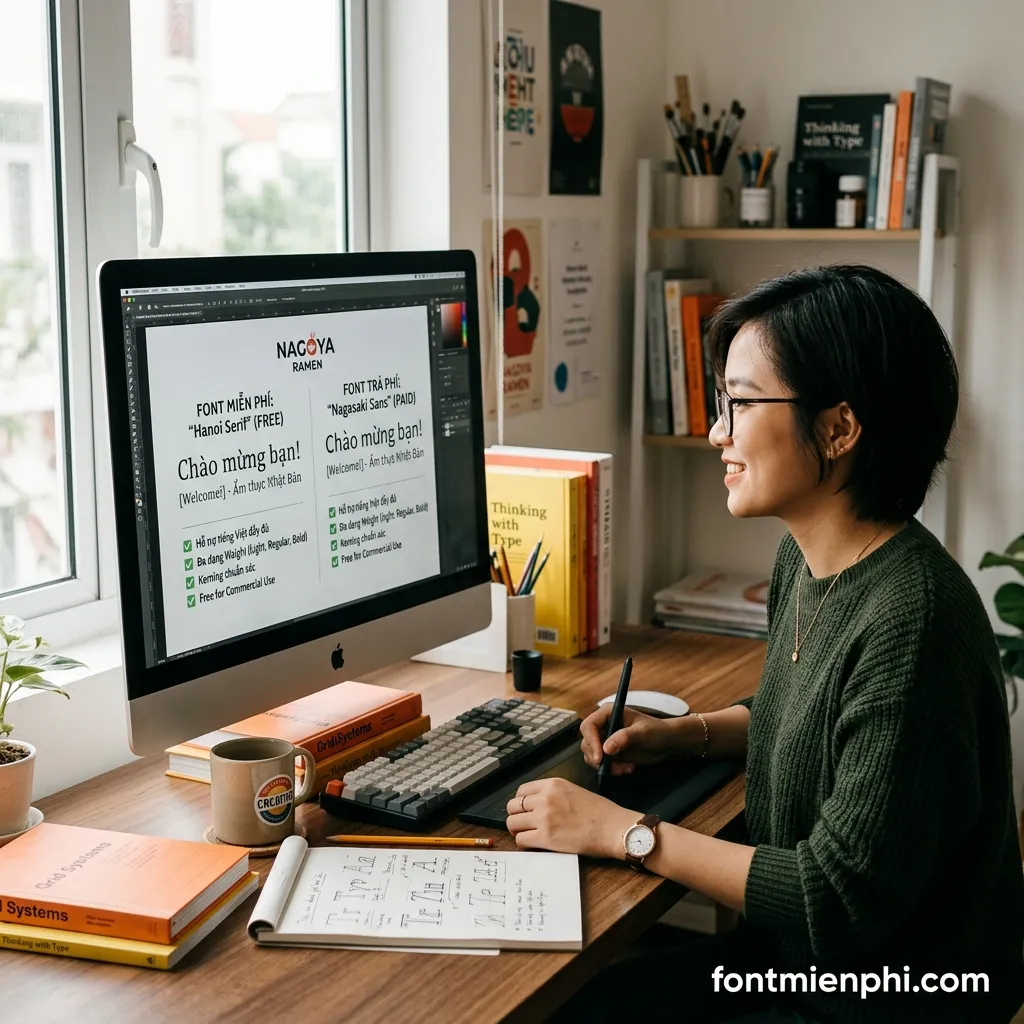
Tiêu chí đánh giá một font miễn phí có đủ “xịn” hay không
Một font miễn phí đáng dùng không chỉ nằm ở cảm giác đẹp khi nhìn lướt qua. Designer chuyên nghiệp thường đánh giá font dựa trên nhiều yếu tố: độ dễ đọc, khoảng cách chữ, độ cân bằng giữa các ký tự, số lượng weight, hỗ trợ tiếng Việt, giấy phép thương mại và tính linh hoạt trong các bối cảnh ứng dụng khác nhau.
Với thị trường Việt Nam, hỗ trợ tiếng Việt là tiêu chí cực kỳ quan trọng. Một font đẹp nhưng thiếu dấu tiếng Việt hoặc hiển thị dấu không cân đối sẽ gây mất chuyên nghiệp ngay lập tức. Khi chọn font, cần kiểm tra kỹ các ký tự như ă, â, ê, ô, ơ, ư, đ và những tổ hợp dấu nặng, hỏi, ngã, sắc, huyền trong câu dài.
Khi nào nên dùng font miễn phí thay vì mua font trả phí
Font miễn phí rất phù hợp với các dự án cần tốc độ triển khai, ngân sách hạn chế hoặc đang ở giai đoạn thử nghiệm phong cách. Ví dụ, một landing page chạy chiến dịch ngắn hạn, bộ template mạng xã hội, bài thuyết trình thương hiệu, blog cá nhân, hồ sơ năng lực freelancer hoặc dự án MVP đều có thể tận dụng font miễn phí chất lượng cao.
Tuy nhiên, điều đó không có nghĩa font miễn phí chỉ dành cho dự án nhỏ. Nhiều thương hiệu lớn vẫn sử dụng font open source vì tính ổn định, khả năng nhúng web thuận tiện và hiệu suất tốt. Các bộ font như Inter, Source Sans, IBM Plex, Noto Sans hay Montserrat đã xuất hiện trong vô số sản phẩm số chuyên nghiệp trên toàn thế giới.
Font trả phí vẫn có lợi thế ở tính độc quyền, chất lượng hoàn thiện rất sâu, nhiều biến thể đặc biệt và dịch vụ hỗ trợ từ foundry. Nhưng nếu mục tiêu là tạo ra thiết kế đẹp, rõ ràng, hiện đại và dễ triển khai, một bộ font miễn phí được chọn đúng hoàn toàn có thể mang lại kết quả không thua kém font thương mại.
Nhóm Font Sans Serif Miễn Phí Cho Website, App Và Nhận Diện Hiện Đại
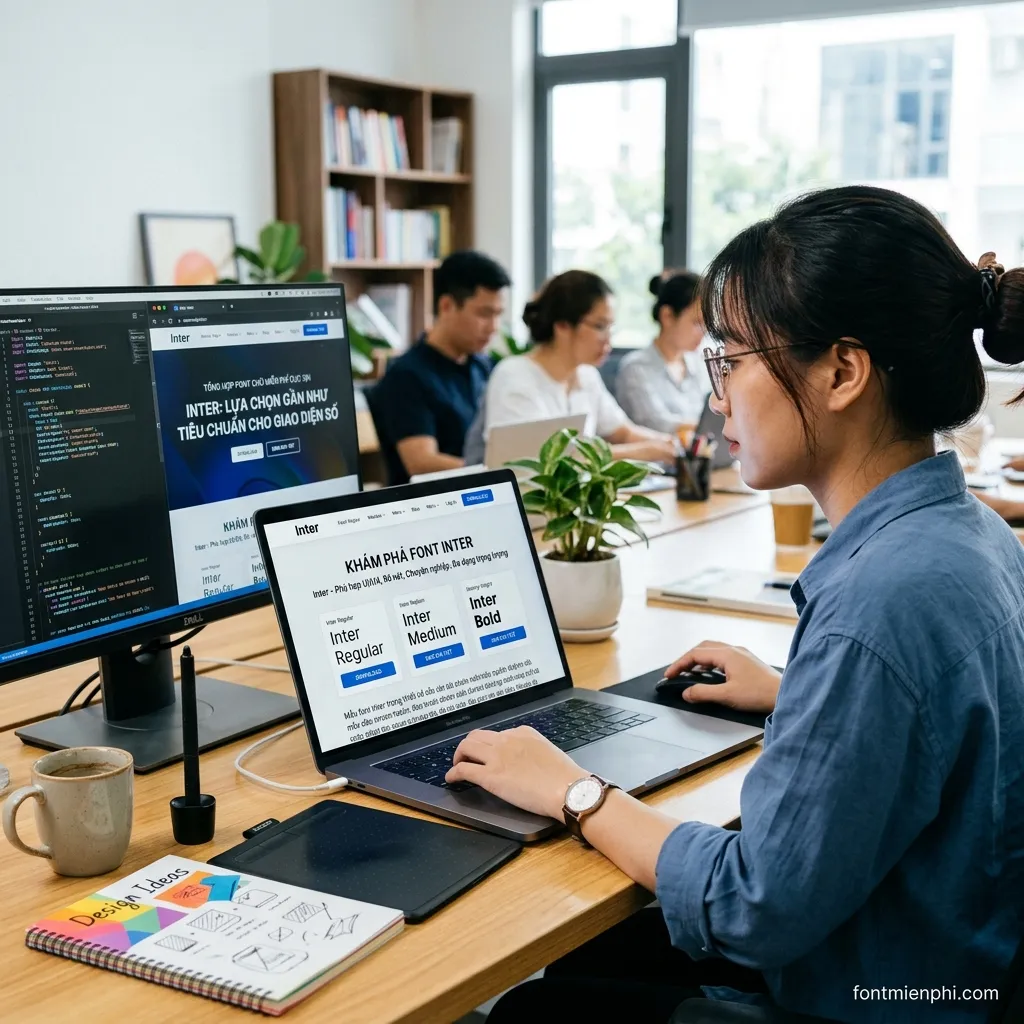
Inter: lựa chọn gần như tiêu chuẩn cho giao diện số
Inter là một trong những font sans serif miễn phí nổi bật nhất hiện nay, đặc biệt phù hợp cho website, dashboard, ứng dụng SaaS, mobile app và hệ thống thiết kế. Font được tối ưu cho màn hình, có độ cao chữ hợp lý, khoảng cách thoáng và khả năng đọc tốt ở kích thước nhỏ. Đây là lý do Inter thường được xem như lựa chọn an toàn nhưng vẫn rất chuyên nghiệp.
Điểm đáng giá của Inter là bộ weight phong phú, hỗ trợ variable font và hoạt động hiệu quả trong nhiều cấp độ nội dung, từ menu, button, form label đến tiêu đề lớn. Khi dùng cho giao diện sản phẩm, Inter giúp tổng thể trở nên gọn gàng, trung tính và đáng tin cậy, không lấn át nội dung nhưng vẫn giữ được cảm giác hiện đại.
– Phù hợp với website công nghệ, SaaS, fintech, dashboard, mobile app
– Ưu điểm nổi bật là dễ đọc, nhiều weight, hỗ trợ web tốt
– Nên dùng khi cần một font trung tính, sạch, ít rủi ro về thẩm mỹ
Manrope: tối giản nhưng có cá tính hơn font UI thông thường
Manrope là font sans serif miễn phí có phong cách hiện đại, tối giản nhưng không quá lạnh. So với nhiều font giao diện phổ biến, Manrope có cấu trúc hình học rõ hơn, đường nét mở và cảm giác thân thiện. Font này rất hợp với thương hiệu công nghệ, giáo dục trực tuyến, sản phẩm tài chính trẻ trung hoặc các landing page muốn tạo ấn tượng cao cấp.
Manrope hoạt động tốt ở cả tiêu đề lẫn đoạn văn. Khi dùng cho heading, font tạo cảm giác chắc chắn và gọn gàng. Khi dùng cho body text, nó vẫn giữ được độ đọc ổn nếu thiết lập line-height hợp lý. Với tiếng Việt, Manrope hỗ trợ khá tốt và có thể dùng trong nhiều dự án thương mại mà không cần lo lắng về chi phí bản quyền.
Để Manrope phát huy hiệu quả, nên kết hợp với bố cục rộng rãi, nhiều khoảng trắng và bảng màu tinh giản. Font này không cần quá nhiều hiệu ứng trang trí; chính sự cân bằng giữa hình học và độ mềm vừa phải đã đủ tạo nên cảm giác cao cấp.
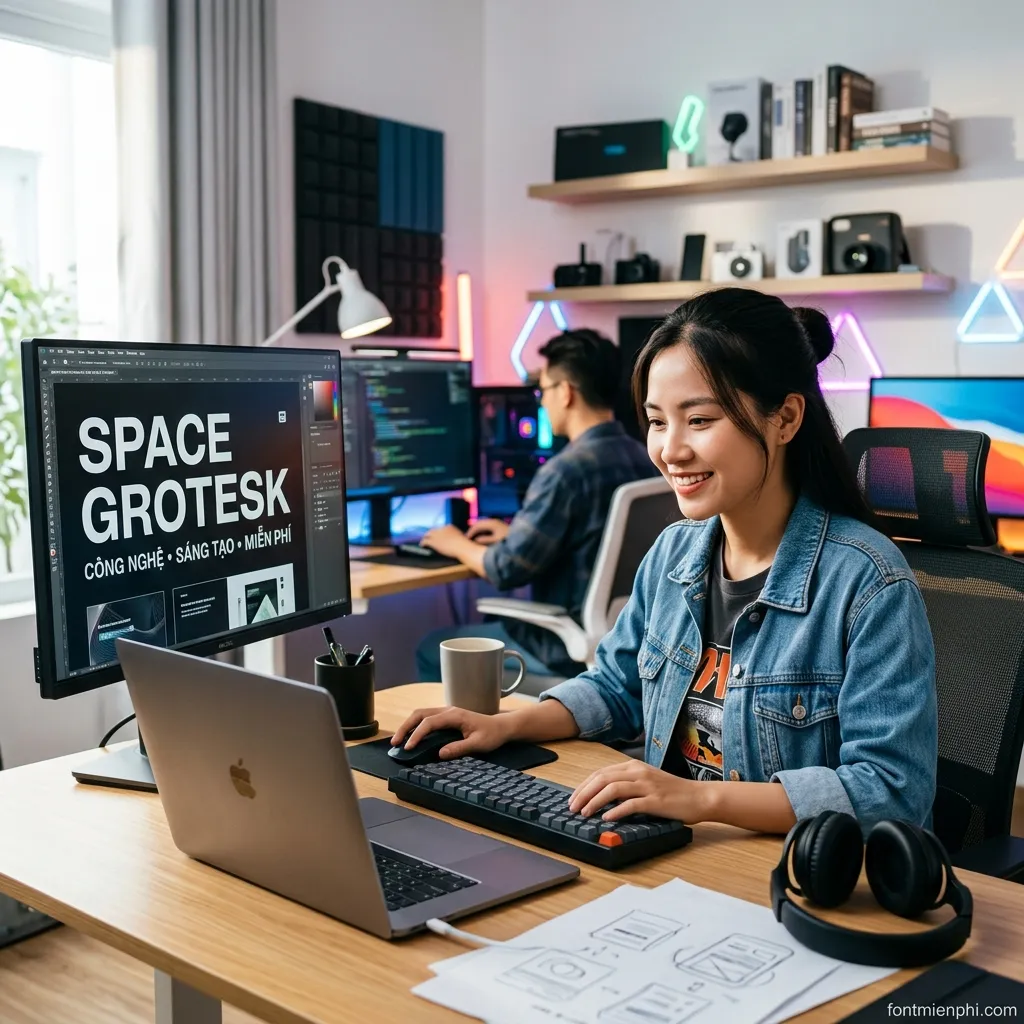
Space Grotesk: font miễn phí có chất công nghệ và sáng tạo
Space Grotesk là lựa chọn tuyệt vời khi bạn muốn thiết kế mang tinh thần tương lai, công nghệ, sáng tạo hoặc hơi experimental nhưng vẫn đảm bảo khả năng đọc. Font có dáng chữ rộng, một số chi tiết đặc trưng ở ký tự tạo cảm giác khác biệt so với các sans serif thông thường. Đây là font rất hợp cho tiêu đề, poster kỹ thuật số, portfolio sáng tạo và website studio.
Khi dùng Space Grotesk, nên chú ý không lạm dụng ở đoạn văn quá dài nếu kích thước chữ nhỏ. Font này tỏa sáng nhất ở headline, navigation, hero section, card title hoặc quote ngắn. Có thể kết hợp Space Grotesk cho tiêu đề với một font body trung tính hơn như Source Sans 3, Noto Sans hoặc IBM Plex Sans để cân bằng giữa cá tính và độ dễ đọc.
– Phù hợp với portfolio, agency, startup AI, sản phẩm sáng tạo
– Nên dùng cho tiêu đề lớn, hero text, poster, banner và social media
– Có thể tạo cảm giác cao cấp nếu đi cùng màu sắc tối giản và layout mạnh
IBM Plex Sans: chuyên nghiệp, đáng tin cậy và giàu tính hệ thống
IBM Plex Sans là một phần trong hệ font IBM Plex nổi tiếng, được thiết kế để thể hiện tinh thần công nghệ, kỹ thuật và sự minh bạch. Đây là font miễn phí có chất lượng rất cao, nhiều weight, hỗ trợ nhiều ngôn ngữ và phù hợp với những thương hiệu cần cảm giác nghiêm túc, đáng tin cậy nhưng không cứng nhắc.
Ưu điểm của IBM Plex Sans là khả năng xây dựng hệ thống typography đồng bộ. Bạn có thể dùng IBM Plex Sans cho giao diện, IBM Plex Serif cho nội dung editorial và IBM Plex Mono cho code hoặc dữ liệu kỹ thuật. Sự thống nhất giữa các biến thể giúp thương hiệu có chiều sâu hơn mà vẫn tiết kiệm chi phí.
Trong các dự án B2B, tài chính, công nghệ, giáo dục hoặc tài liệu chuyên môn, IBM Plex Sans mang lại cảm giác rất “đúng chỗ”. Nó không quá thời trang để nhanh lỗi mốt, cũng không quá phổ thông đến mức nhạt nhòa. Đây là lựa chọn đáng cân nhắc nếu bạn cần một font miễn phí có độ tin cậy cao.
Nhóm Font Serif Và Display Miễn Phí Cho Thương Hiệu Cao Cấp
Playfair Display: vẻ đẹp editorial cho tiêu đề sang trọng
Playfair Display là font serif miễn phí rất nổi tiếng, thường được dùng cho thời trang, mỹ phẩm, nghệ thuật, nhà hàng cao cấp, wedding branding và các thiết kế cần cảm giác thanh lịch. Font có độ tương phản nét cao, dáng chữ mềm mại và tạo ấn tượng mạnh khi đặt ở kích thước lớn.
Điểm cần lưu ý là Playfair Display không phải lựa chọn tối ưu cho đoạn văn dài trên màn hình nhỏ. Font phù hợp hơn cho headline, quote, logo dạng chữ, bìa catalogue hoặc tiêu đề section. Khi kết hợp với sans serif hiện đại như Lato, Source Sans 3 hoặc Work Sans, Playfair Display có thể tạo nên cặp typography cân bằng giữa cổ điển và hiện đại.
Với tiếng Việt, cần kiểm tra kỹ từng phiên bản và nguồn tải để đảm bảo dấu hiển thị đẹp. Trong thiết kế thương hiệu cao cấp, chỉ một dấu tiếng Việt bị lệch hoặc quá sát ký tự cũng có thể làm giảm đáng kể cảm giác chuyên nghiệp của toàn bộ ấn phẩm.
Cormorant Garamond: tinh tế, cổ điển và giàu cảm xúc
Cormorant Garamond là font serif miễn phí lấy cảm hứng từ phong cách Garamond cổ điển, nhưng được diễn giải theo hướng sắc sảo và giàu tính trình diễn hơn. Font này đặc biệt phù hợp với các dự án văn hóa, nghệ thuật, xuất bản, thương hiệu thủ công, thời trang boutique và thiết kế cần chiều sâu thẩm mỹ.
Khi dùng Cormorant Garamond, nên khai thác các weight nhẹ hoặc semi-bold cho tiêu đề lớn để tạo cảm giác tinh tế. Font có nét thanh mảnh, độ tương phản cao nên cần tránh đặt trên nền quá phức tạp hoặc dùng kích thước quá nhỏ. Với layout phù hợp, Cormorant Garamond có thể tạo cảm giác đắt tiền không kém nhiều font serif thương mại.
– Phù hợp với thương hiệu nghệ thuật, thời trang, sách, văn hóa, thủ công
– Nên dùng trong heading, quote, logo chữ, tiêu đề catalogue
– Kết hợp tốt với sans serif đơn giản để tránh tổng thể bị quá cổ điển
Bodoni 72 và Libre Bodoni: chất thời trang mạnh mẽ
Bodoni là phong cách serif kinh điển gắn liền với thời trang, tạp chí, mỹ phẩm và thiết kế luxury. Trong nhóm font miễn phí, Libre Bodoni là lựa chọn đáng chú ý nhờ giữ được tinh thần tương phản cao, nét dọc mạnh và vẻ ngoài sang trọng. Nếu muốn tạo headline có cảm giác thời thượng, Libre Bodoni có thể là một phương án rất hiệu quả.
Tuy nhiên, font kiểu Bodoni cần được dùng có kiểm soát. Độ tương phản nét quá cao khiến chữ dễ mất chi tiết khi in nhỏ hoặc hiển thị trên màn hình độ phân giải thấp. Vì vậy, nên ưu tiên dùng cho tiêu đề lớn, logo, poster, bìa lookbook hoặc các điểm nhấn thị giác thay vì dùng cho body text dài.
Khi phối Libre Bodoni với một sans serif tối giản, thiết kế sẽ có sự căng đối thú vị giữa cổ điển và hiện đại. Đây là công thức phổ biến trong ngành thời trang: serif cao cấp cho cảm xúc thương hiệu, sans serif sạch cho thông tin chức năng.
Abril Fatface: nổi bật, đậm chất poster và rất dễ ghi nhớ
Abril Fatface là font display miễn phí có cá tính mạnh, nét dày, độ tương phản cao và khả năng tạo điểm nhấn tức thì. Font này phù hợp với tiêu đề quảng cáo, poster sự kiện, banner mạng xã hội, bìa blog hoặc các thiết kế cần thu hút ánh nhìn trong thời gian ngắn.
Khác với những font serif thanh lịch, Abril Fatface mang cảm giác táo bạo và giàu năng lượng hơn. Nó có thể làm một layout đơn giản trở nên nổi bật chỉ bằng một dòng tiêu đề lớn. Tuy nhiên, vì cá tính quá rõ, font này nên được dùng tiết chế. Nếu dùng quá nhiều, thiết kế dễ trở nên nặng nề và khó đọc.
– Phù hợp với poster, campaign, social media, tiêu đề blog, sự kiện
– Nên dùng ở kích thước lớn với số lượng chữ vừa phải
– Kết hợp tốt với sans serif nhẹ, khoảng trắng lớn và màu nền có chủ đích
Nhóm Font Miễn Phí Hỗ Trợ Tiếng Việt Tốt Cho Nội Dung Dài
Noto Sans và Noto Serif: giải pháp an toàn cho dự án đa ngôn ngữ
Noto là hệ font miễn phí do Google phát triển với mục tiêu hỗ trợ gần như toàn bộ hệ chữ trên thế giới. Với tiếng Việt, Noto Sans và Noto Serif là hai lựa chọn rất đáng tin cậy vì dấu hiển thị ổn định, ký tự đầy đủ và khả năng đọc tốt trong nhiều môi trường khác nhau.
Noto Sans phù hợp với website tin tức, blog, tài liệu hướng dẫn, giao diện ứng dụng và các hệ thống cần độ rõ ràng cao. Noto Serif phù hợp hơn với bài viết dài, nội dung học thuật, xuất bản số hoặc những dự án muốn tạo cảm giác nghiêm túc, truyền thống hơn. Cả hai đều không quá phô diễn, nhưng chính sự trung tính đó lại giúp nội dung trở thành trung tâm.
Đối với SEO và trải nghiệm đọc, một font ổn định như Noto có giá trị rất lớn. Người dùng ở các thiết bị khác nhau vẫn thấy chữ rõ, dấu không lỗi và đoạn văn không bị vỡ nhịp. Đây là yếu tố thường bị xem nhẹ, nhưng lại ảnh hưởng trực tiếp đến thời gian ở lại trang và khả năng tiếp nhận nội dung.
Source Sans 3: cân bằng giữa thân thiện và chuyên nghiệp
Source Sans 3 là phiên bản phát triển từ Source Sans Pro, một font sans serif miễn phí rất được ưa chuộng trong thiết kế giao diện và nội dung số. Font có dáng chữ mở, khoảng cách dễ chịu, hỗ trợ nhiều weight và hiển thị tốt ở kích thước nhỏ. Đây là lựa chọn phù hợp cho website doanh nghiệp, blog chuyên môn, trang dịch vụ và tài liệu trực tuyến.
So với một số font geometric sans, Source Sans 3 có cảm giác nhân văn và dễ đọc hơn trong đoạn văn dài. Nó không gây mỏi mắt, không quá cá tính và hoạt động tốt với nhiều ngành nghề. Nếu bạn cần một font body đáng tin cậy để đi cùng display font mạnh ở phần tiêu đề, Source Sans 3 là lựa chọn rất thực tế.
– Phù hợp với blog, website doanh nghiệp, tài liệu, landing page, app
– Ưu điểm là dễ đọc, trung tính, hỗ trợ tiếng Việt tốt
– Có thể kết hợp với Playfair Display, Space Grotesk hoặc Cormorant Garamond
Literata: font đọc dài có chiều sâu và phù hợp nội dung editorial
Literata là font serif miễn phí được thiết kế với mục tiêu phục vụ trải nghiệm đọc, đặc biệt trong môi trường sách điện tử và nội dung dài. Font có nhịp chữ ổn định, nét không quá mảnh, dáng chữ ấm và tạo cảm giác tin cậy. Với các website chuyên về phân tích, giáo dục, văn hóa, sách hoặc nội dung chuyên sâu, Literata là lựa chọn rất đáng thử.
Điểm hay của Literata là nó mang cảm giác editorial nhưng không quá kiểu cách. Người đọc có thể theo dõi bài viết dài mà không bị phân tâm bởi hình dáng chữ. So với các display serif hào nhoáng, Literata kín đáo hơn, nhưng lại bền vững hơn khi dùng cho hệ thống nội dung lớn.
Khi thiết lập Literata cho web, nên chú ý line-height rộng vừa phải và độ dài dòng không quá lớn. Một đoạn văn khoảng 60 đến 75 ký tự mỗi dòng thường giúp người đọc theo dõi dễ hơn. Nếu dùng trên mobile, cần kiểm tra kích thước chữ và khoảng cách dòng để tránh cảm giác chật.
Be Vietnam Pro: lựa chọn bản địa hóa tốt cho thương hiệu Việt
Be Vietnam Pro là font sans serif miễn phí được thiết kế với sự chú trọng đến tiếng Việt, vì vậy đây là lựa chọn rất đáng cân nhắc cho các thương hiệu hoạt động tại Việt Nam. Font có dáng hiện đại, rõ ràng, hỗ trợ nhiều weight và hiển thị dấu tiếng Việt cân đối hơn nhiều font quốc tế không được tối ưu riêng cho ngôn ngữ này.
Be Vietnam Pro phù hợp với website doanh nghiệp, ứng dụng, sản phẩm giáo dục, thương mại điện tử, tài liệu thương hiệu và thiết kế truyền thông. Font tạo cảm giác hiện đại nhưng vẫn gần gũi, không quá lạnh như một số font công nghệ. Đây là ưu điểm lớn khi thương hiệu muốn vừa chuyên nghiệp vừa dễ tiếp cận.
Trong hệ thống nhận diện, Be Vietnam Pro có thể dùng làm font chính cho cả tiêu đề và thân bài nếu muốn giữ sự nhất quán. Khi cần điểm nhấn cao cấp hơn, có thể phối nó với một serif miễn phí như Cormorant Garamond hoặc Literata, miễn là kiểm soát tốt độ tương phản giữa hai phong cách.
Cách Phối Và Ứng Dụng Font Miễn Phí Để Trông Như Font Trả Phí
Chọn font theo vai trò thay vì chọn theo cảm tính
Một lỗi phổ biến khi dùng font miễn phí là chọn quá nhiều font chỉ vì thấy từng font đều đẹp. Trong thiết kế chuyên nghiệp, font cần được phân vai rõ ràng: font cho tiêu đề, font cho đoạn văn, font cho nhãn nhỏ, font cho số liệu hoặc font cho điểm nhấn. Khi mỗi font có nhiệm vụ cụ thể, tổng thể sẽ trông có hệ thống hơn rất nhiều.
Công thức an toàn là dùng tối đa hai họ font trong một dự án: một font chính cho nội dung chức năng và một font phụ cho điểm nhấn thương hiệu. Ví dụ, có thể dùng Source Sans 3 cho body text và Playfair Display cho heading; Manrope cho giao diện và Cormorant Garamond cho quote; IBM Plex Sans cho hệ thống thông tin và IBM Plex Mono cho dữ liệu kỹ thuật.
Thay vì hỏi “font này có đẹp không”, nên hỏi “font này có giải quyết đúng mục tiêu truyền thông không”. Một thương hiệu luật cần sự tin cậy sẽ không dùng cùng kiểu chữ với một festival âm nhạc. Một app tài chính cần rõ ràng sẽ có nhu cầu khác với một lookbook thời trang. Khi font được chọn theo chiến lược, thiết kế sẽ tự nhiên trông đắt giá hơn.
Tối ưu kích thước, khoảng cách và độ tương phản
Chất lượng typography không chỉ đến từ file font mà còn đến từ cách thiết lập. Một font đắt tiền vẫn có thể trông nghiệp dư nếu line-height quá chật, letter-spacing sai hoặc cấp bậc tiêu đề không rõ. Ngược lại, một font miễn phí được căn chỉnh cẩn thận có thể tạo cảm giác tinh tế và cao cấp.
Với đoạn văn trên web, kích thước chữ thường nên nằm trong khoảng dễ đọc, line-height đủ thoáng và chiều rộng cột không quá dài. Với tiêu đề, cần tạo sự khác biệt rõ so với body text bằng kích thước, weight, khoảng cách hoặc màu sắc. Không nhất thiết phải dùng nhiều hiệu ứng; chỉ cần phân cấp tốt, người đọc đã cảm nhận được sự chuyên nghiệp.
Letter-spacing cũng cần dùng đúng chỗ. Chữ in hoa có thể cần tăng khoảng cách nhẹ để thoáng hơn, trong khi chữ thường ở đoạn văn dài thường không nên giãn quá nhiều. Với các font display như Abril Fatface, Playfair Display hoặc Libre Bodoni, việc tinh chỉnh khoảng cách tiêu đề có thể tạo khác biệt lớn về cảm giác cao cấp.
Kiểm tra license và nguồn tải trước khi đưa vào dự án thật
Nguồn tải font ảnh hưởng trực tiếp đến độ an toàn của dự án. Nên ưu tiên các nền tảng uy tín như Google Fonts, Fontshare, Adobe Fonts miễn phí theo gói, GitHub chính thức của dự án hoặc website của nhà thiết kế. Tránh tải font từ những trang không rõ nguồn gốc vì có thể gặp file lỗi, license không chính xác hoặc thậm chí rủi ro bảo mật.
Trước khi dùng trong logo, bao bì, website thương mại hoặc sản phẩm bán ra thị trường, cần đọc license gốc. Các giấy phép phổ biến như SIL Open Font License thường cho phép sử dụng thương mại khá rộng rãi, nhưng vẫn có điều kiện về việc phân phối lại, chỉnh sửa hoặc đổi tên font. Không nên chỉ dựa vào dòng mô tả “free” trên một trang tải lại.
– Kiểm tra font có miễn phí cho thương mại hay chỉ cá nhân
– Xác minh có được nhúng web, dùng trong app, dùng trong logo hay không
– Lưu lại file license trong thư mục dự án để dễ đối chiếu về sau
Những cặp font miễn phí đáng thử cho nhiều phong cách thiết kế
Nếu muốn tạo cảm giác hiện đại và sạch sẽ, Manrope kết hợp với Source Sans 3 là một cặp dễ dùng. Manrope có thể đảm nhiệm heading, còn Source Sans 3 xử lý đoạn văn dài. Cặp này phù hợp với website startup, landing page sản phẩm, khóa học trực tuyến và thương hiệu dịch vụ chuyên nghiệp.
Với phong cách cao cấp, Playfair Display kết hợp với Be Vietnam Pro tạo sự cân bằng tốt giữa vẻ editorial và khả năng đọc tiếng Việt. Playfair Display nên dùng cho tiêu đề lớn hoặc điểm nhấn, trong khi Be Vietnam Pro giữ vai trò nội dung chính. Đây là lựa chọn hợp với mỹ phẩm, spa, thời trang, studio ảnh và thương hiệu cá nhân.
Với dự án công nghệ hoặc dữ liệu, IBM Plex Sans kết hợp IBM Plex Mono giúp tạo hệ thống rõ ràng, nhất quán và đáng tin cậy. IBM Plex Sans dùng cho giao diện và nội dung, IBM Plex Mono dùng cho mã, số liệu, nhãn kỹ thuật hoặc chi tiết mang tính hệ thống. Cặp này đặc biệt hợp với SaaS, fintech, AI tool và sản phẩm B2B.
Với nội dung dài mang tính tri thức, Literata kết hợp Noto Sans là một công thức bền vững. Literata tạo nhịp đọc ấm và có chiều sâu cho bài viết chính, còn Noto Sans hỗ trợ menu, caption, chú thích và thành phần giao diện. Cách phối này hợp với blog chuyên sâu, tạp chí điện tử, website giáo dục và dự án xuất bản số.
Lưu ý khi dùng font miễn phí cho logo và nhận diện thương hiệu
Khi dùng font miễn phí cho logo, vấn đề lớn nhất không phải là chất lượng mà là tính phổ biến. Một font miễn phí nổi tiếng có thể đã được hàng nghìn thương hiệu khác sử dụng. Để logo không bị đại trà, designer nên tùy biến chữ một cách hợp pháp, chẳng hạn chỉnh khoảng cách, tinh chỉnh một vài nét, tạo ligature riêng hoặc kết hợp với biểu tượng độc quyền.
Việc tùy biến cần được thực hiện cẩn thận để không phá vỡ cấu trúc chữ. Một chỉnh sửa nhỏ ở đầu nét, đuôi chữ, khoảng âm hoặc tỷ lệ ký tự có thể giúp logo khác biệt hơn nhưng vẫn giữ được sự cân bằng. Trước khi chỉnh sửa font, cần kiểm tra license để biết có được phép tạo tác phẩm phái sinh hoặc chỉnh sửa file font hay không.
Font miễn phí có thể là nền tảng rất tốt cho nhận diện, nhưng hệ thống thương hiệu không nên phụ thuộc hoàn toàn vào một font. Màu sắc, bố cục, hình ảnh, giọng văn, icon, motion và quy chuẩn sử dụng cũng góp phần tạo nên cảm giác cao cấp. Khi toàn bộ hệ thống được thiết kế nhất quán, font miễn phí sẽ hòa vào trải nghiệm thương hiệu một cách tự nhiên.
Danh sách nhanh các font miễn phí nên lưu vào thư viện thiết kế
– Inter: mạnh về giao diện số, dashboard, app và website công nghệ
– Manrope: hiện đại, tối giản, phù hợp landing page và thương hiệu trẻ
– Space Grotesk: cá tính, sáng tạo, hợp tiêu đề và sản phẩm công nghệ
– IBM Plex Sans: chuyên nghiệp, hệ thống, phù hợp B2B và tài liệu kỹ thuật
– Source Sans 3: dễ đọc, linh hoạt, tốt cho body text và website doanh nghiệp
– Noto Sans: an toàn cho tiếng Việt, đa ngôn ngữ và nội dung dài
– Noto Serif: nghiêm túc, ổn định, hợp nội dung học thuật và editorial
– Be Vietnam Pro: tối ưu cho tiếng Việt, phù hợp thương hiệu Việt hiện đại
– Playfair Display: sang trọng, hợp tiêu đề thời trang, mỹ phẩm, lifestyle
– Cormorant Garamond: cổ điển, tinh tế, hợp nghệ thuật và xuất bản
– Libre Bodoni: thời thượng, mạnh về headline luxury và lookbook
– Abril Fatface: nổi bật, giàu năng lượng, hợp poster và chiến dịch truyền thông
Cách xây dựng thư viện font miễn phí cho quy trình làm việc lâu dài
Thay vì tải thật nhiều font rồi để rải rác trong máy, nên xây dựng một thư viện có chọn lọc theo nhóm nhu cầu. Có thể chia thành font UI, font body, font heading, font serif cao cấp, font display, font mono và font hỗ trợ tiếng Việt tốt. Cách tổ chức này giúp quá trình chọn font nhanh hơn và giảm nguy cơ dùng sai phong cách.
Mỗi font trong thư viện nên đi kèm ghi chú ngắn về nguồn tải, license, mức độ hỗ trợ tiếng Việt, dự án phù hợp và các cặp font đề xuất. Khi bắt đầu một thiết kế mới, bạn chỉ cần lọc theo mục tiêu thương hiệu thay vì tìm kiếm lại từ đầu. Đây là thói quen nhỏ nhưng giúp quy trình chuyên nghiệp hơn đáng kể.
Một thư viện font miễn phí tốt không cần quá lớn. Khoảng 20 đến 30 font được kiểm tra kỹ, có license rõ ràng và biết rõ cách ứng dụng sẽ hữu ích hơn hàng trăm font tải theo cảm hứng. Khi hiểu đặc tính của từng font, bạn có thể tạo ra nhiều phong cách khác nhau từ cùng một bộ công cụ gọn gàng.
Trong thực tế, sự khác biệt giữa thiết kế nghiệp dư và thiết kế chuyên nghiệp thường nằm ở cách lựa chọn có chủ đích. Một font miễn phí như Be Vietnam Pro, Literata, Manrope hay IBM Plex Sans nếu được đặt trong hệ thống phân cấp rõ ràng, khoảng cách hợp lý và ngữ cảnh thương hiệu phù hợp hoàn toàn có thể tạo nên cảm giác cao cấp, chỉn chu và bền vững theo thời gian.